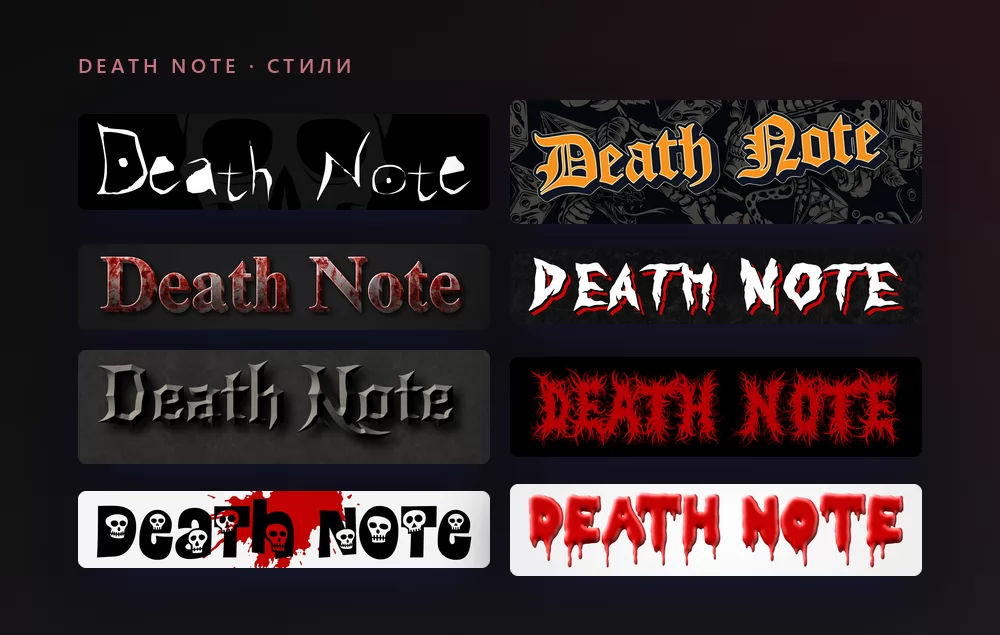
О шрифте Death Note
Death Note («Тетрадь смерти») это японская манга, написанная Цугуми Обой и нарисованная Такэси Обатой, выходившая в журнале Weekly Shonen Jump с 2003 по 2006 год. Старшеклассник Лайт Ягами находит сверхъестественную тетрадь: любой, чьё имя в ней записано, умирает, если пишущий знает его лицо. Его поход за очищение мира от преступников превращается в погоню с детективом, известным только как L. Аниме вышло в 2006 году, затем игровые фильмы в Японии и фильм Netflix в 2017 году.
На обложках и постерах использовались разные надписи, поэтому «шрифт Death Note» для разных людей значит разное. Надпись в названии это рукописная работа, тонкая, исцарапанная, неровная, и она никогда не выпускалась как шрифт. Два бесплатных шрифта воссоздают её вид: Death Font от joshua1985, близкий к обложке манги, и Death Note от Rebirth Organization, ближе к постеру фильма. А буква, которой подписывается L, набрана шрифтом Cloister Black, готической антиквой в стиле Old English.
Одно нужно знать до набора: в Death Font есть только прописные, так что для вида обложки набирать нужно прописными. У генератора такого ограничения нет.
Как сделать текст в стиле Death Note
Шаг 1. Введите слово
Откройте генератор и замените пример своим текстом: имя, название канала, заголовок видео, строка для приглашения на Хэллоуин. Буквы перерисовываются прямо во время набора. Здесь работают и прописные, и строчные, и именно их смесь даёт названию неровный рукописный вид.
Шаг 2. Выберите стиль
Классика это тонкая белая исцарапанная надпись на чёрном, с черепом позади. На вкладке «Стили» заливка, обводка и тень меняются отдельно, так что форму букв можно оставить, а цвета увести в другую сторону: кроваво-красный, или бледно-серый на белом для обложки тетради.
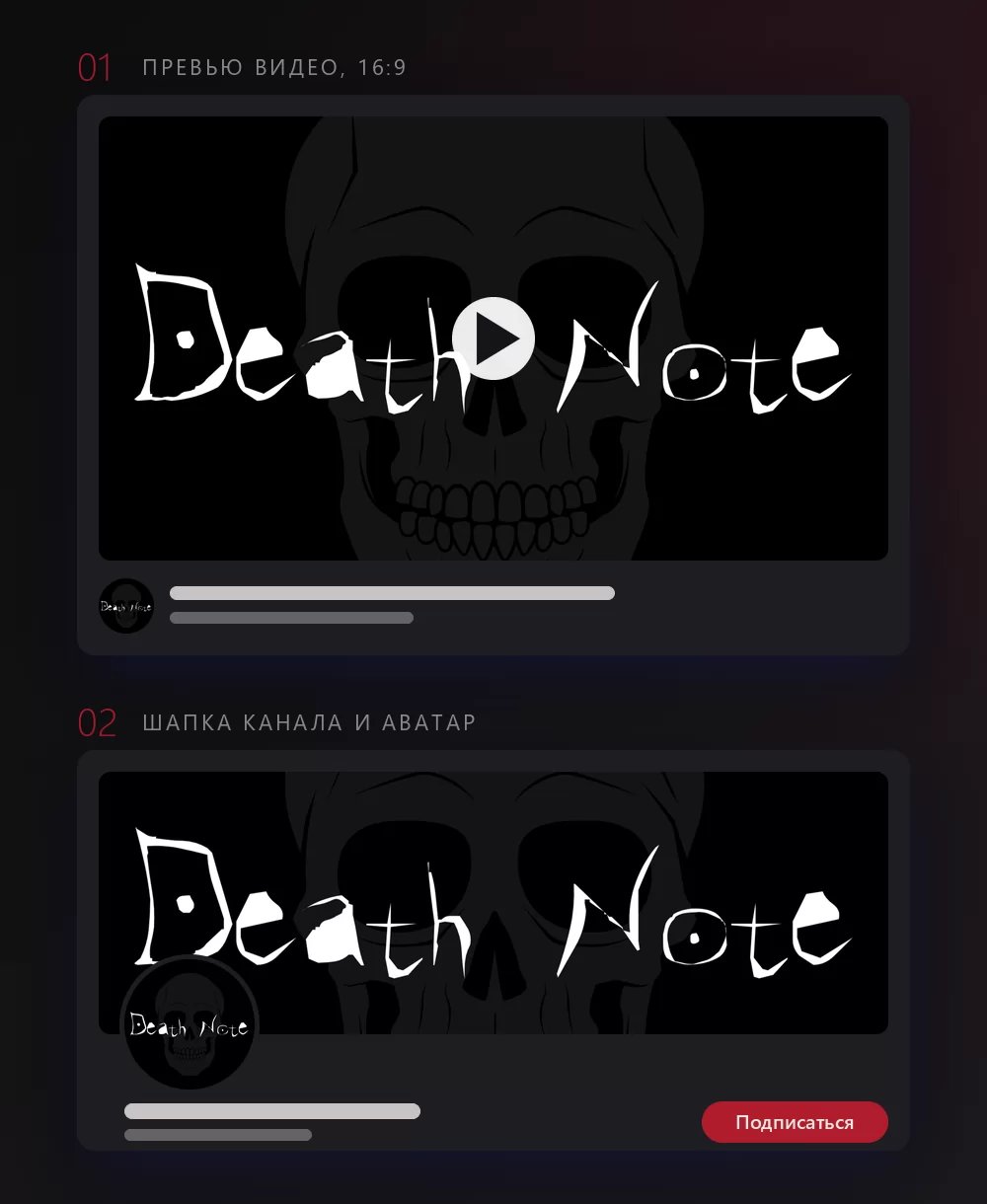
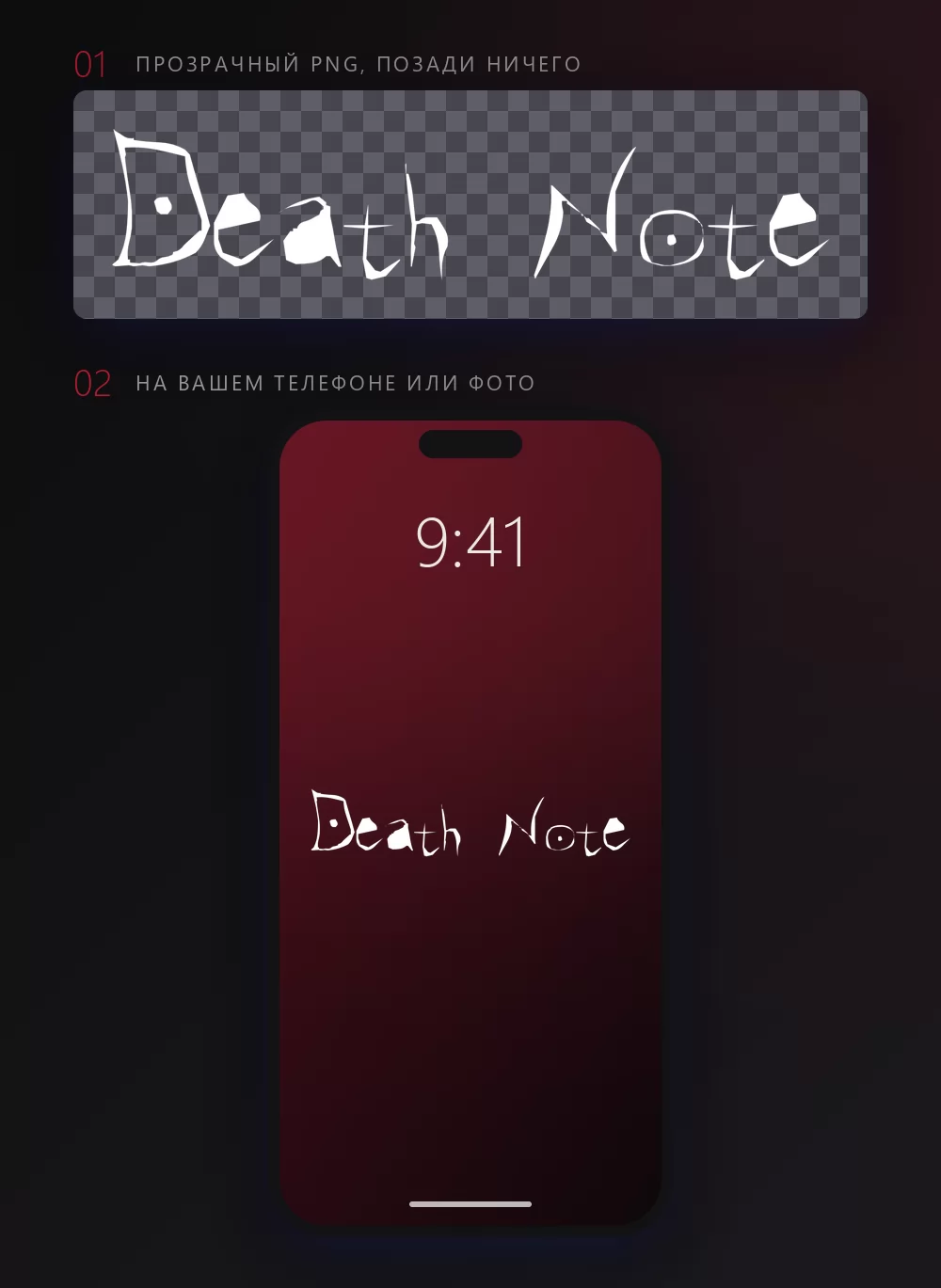
Длинные имена быстро заполняют ширину
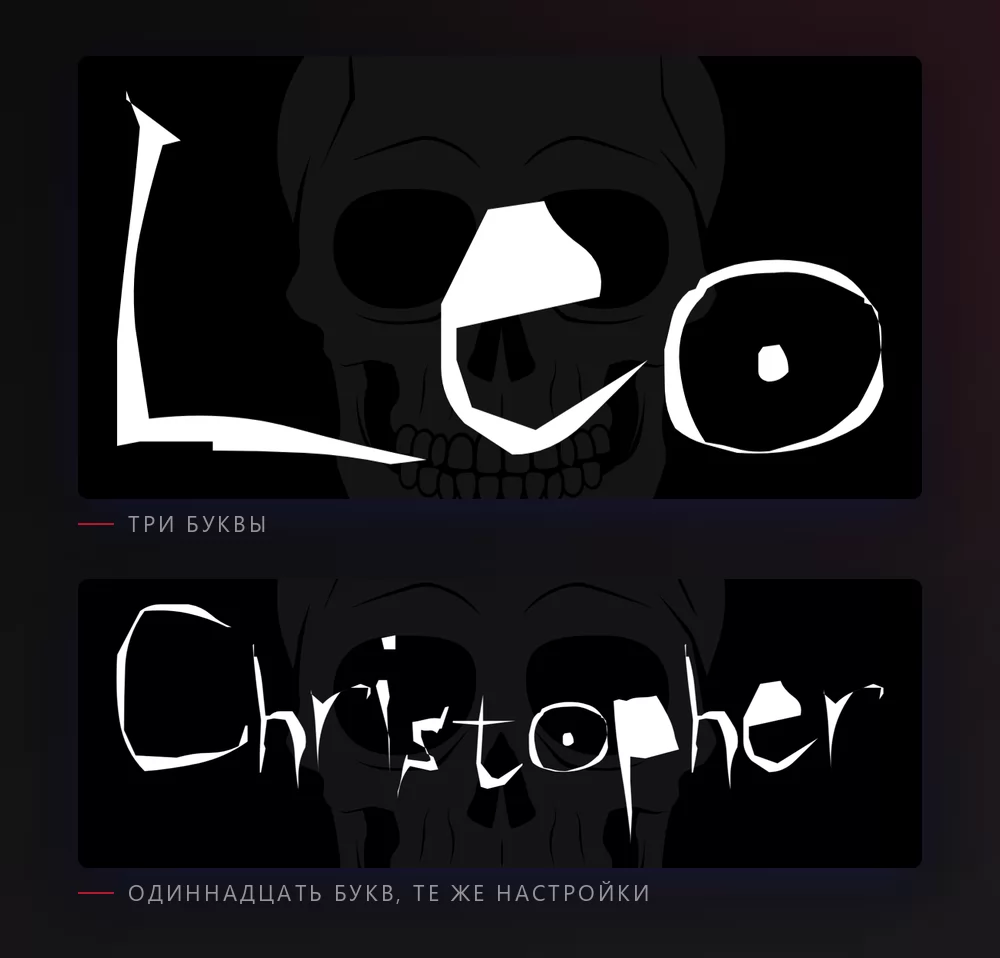
Чем больше букв, тем плотнее они сидят. Межбуквенный интервал это ползунок на вкладке «Текст»: чуть раздвиньте, и длинное имя перестанет выглядеть сжатым. На той же вкладке масштаб, межстрочный интервал, изгиб и поворот.
Стиль логотипа или стиль L
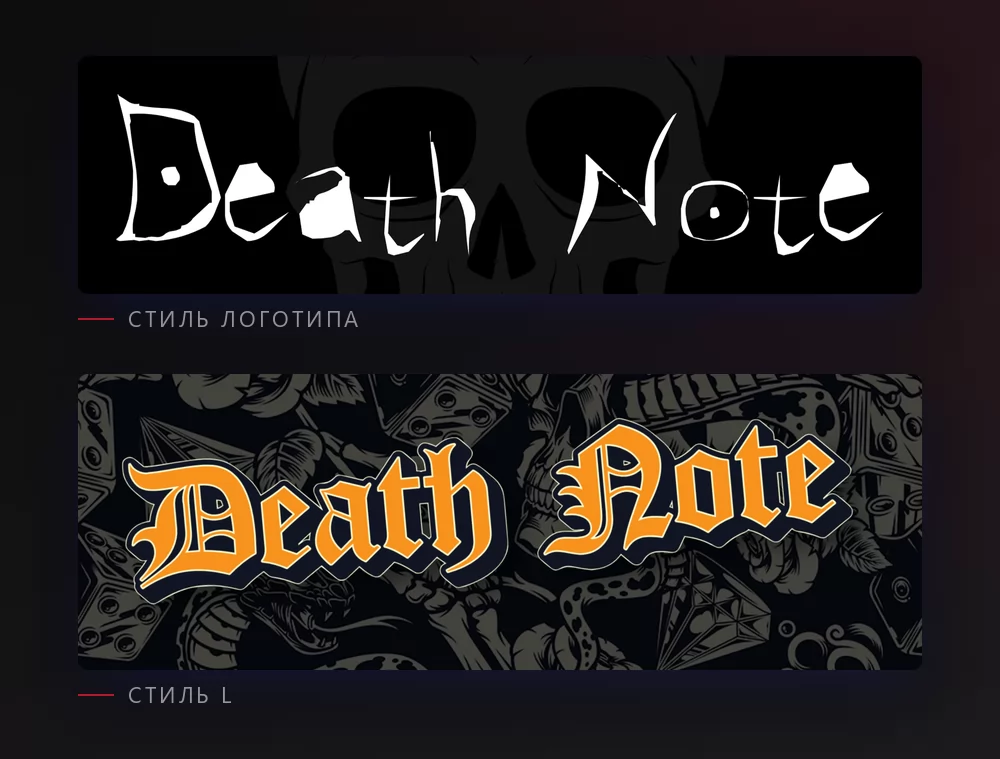
Стиль логотипа это само название: тонкие белые штрихи, будто процарапанные в чёрном, неровная высота, череп, проступающий сзади. Именно это большинство представляет, говоря «шрифт Death Note».
Стиль L это готика подписи детектива, та единственная буква L в стиле Old English, которую он оставляет на экранах и в письмах. В сериале это Cloister Black. Жирная, плотная, готическая, она читается с другого конца комнаты, и к ней стоит обратиться, когда исцарапанное название слишком тонкое для превью. В генераторе готического тату-шрифта она есть как готовый стиль, оранжевая с тёмной обводкой.
Какой шрифт, если вы хотите его установить
Само название это не шрифт. Это рукописный леттеринг, поэтому любой файл с названием «шрифт Death Note» является чьим-то воссозданием.
Death Font от joshua1985 это воссоздание, которым все пользуются для вида обложки. Он лежит на DaFont, указан как полностью бесплатный, больше четырёхсот тысяч скачиваний. Только прописные: наберите строчными, и не получите ничего.
Death Note от Rebirth Organization это второй шрифт, который перечисляют сайты, ближе к постеру игровых фильмов, чем к обложке манги. Это потёртый акцидентный шрифт, на него стоит взглянуть, если нужна изношенная, выветренная версия вместо исцарапанной.
Cloister Black это буква L. Рисунок восходит к Моррису Фуллеру Бентону из American Type Founders, 1904 год, а цифровая версия, которую ставит большинство, принадлежит Дитеру Штеффману и лежит на DaFont как полностью бесплатная, больше пяти миллионов скачиваний. Из трёх она самая полезная, потому что это полноценная, хорошо сделанная готика, которая пригодится снова.
Для работы с клиентами, где лицензия должна быть чистой, честные варианты это готические шрифты с открытой лицензией на Google Fonts: Grenze Gotisch от Omnibus-Type, целое семейство с начертаниями, и UnifrakturMaguntia, ближе к традиционной фрактуре. Ни один из них не шрифт Death Note. Оба дают стиль L с лицензией, которую никто не оспорит.
Что с ним делают на самом деле
Сайты шрифтов перечисляют «лучшие применения», и они правы в том, что встречается чаще всего: превью видео и баннеры каналов для обзоров аниме, приглашения на Хэллоуин, обложки тетрадей для косплея, обои телефона и монтажи с именем персонажа в стиле названия. Всё это лучше работает с прозрачным PNG, чем с установленным шрифтом, потому что эффект названия не в одних буквах: это белое на чёрном, царапины, череп. Файл шрифта даёт контуры и ничего больше.
Почему мой текст выглядит плоским рядом с настоящим названием? Обычно дело в фоне, а не в шрифте. Название это тонкие сероватые штрихи на чёрном с проступающим сзади черепом. На белой странице или с добавленной обводкой оно перестаёт читаться как Death Note.